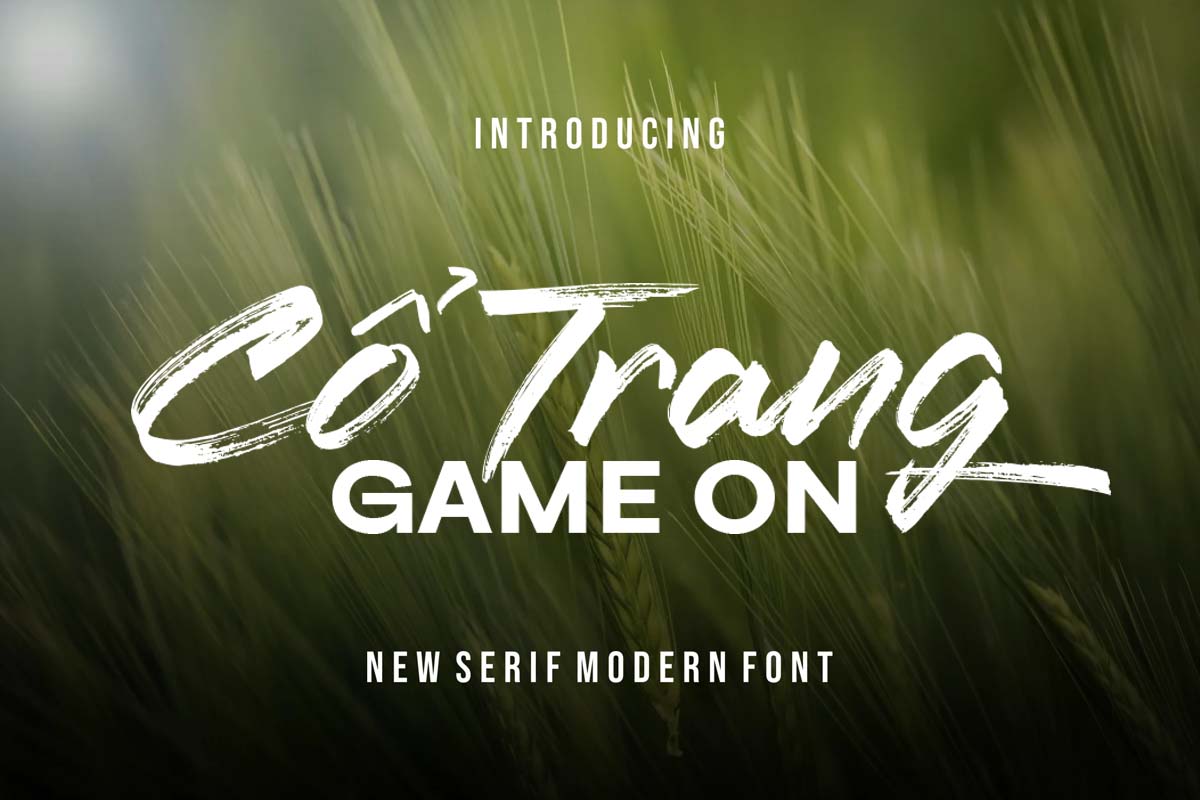
![[Tải Xuống] 13 Font Chữ Nét Cọ Việt Hóa Miễn Phí](https://cdn.s99.vn/cloud/phong-chu-net-co-viet-hoa-anh-6.jpg)
Font chữ nét cọ – hay còn gọi là brush-style font – là dòng chữ được thiết kế mô phỏng theo nét vẽ của cọ vẽ tay, thường có độ dày mỏng không đều, nét quẹt, chảy mực hoặc hiệu ứng thô ráp như thật. Font này mang đậm tính biểu cảm, nghệ thuật và cảm xúc thủ công, tạo nên sự sống động và tự nhiên cho thiết kế.
Khác với font chữ viết tay (script font), vốn thiên về sự liền mạch, uyển chuyển và thanh thoát, font nét cọ thể hiện rõ kết cấu của từng nét vẽ, có thể mềm mại hoặc mạnh mẽ tùy theo phong cách. Sự không hoàn hảo chính là điều tạo nên vẻ cá tính và độc đáo cho loại font này.
Font brush thường được sử dụng trong các thiết kế đòi hỏi sự sáng tạo và cảm xúc – như poster nghệ thuật, typography, tiêu đề nổi bật hoặc các sản phẩm truyền thông mang phong cách thủ công.
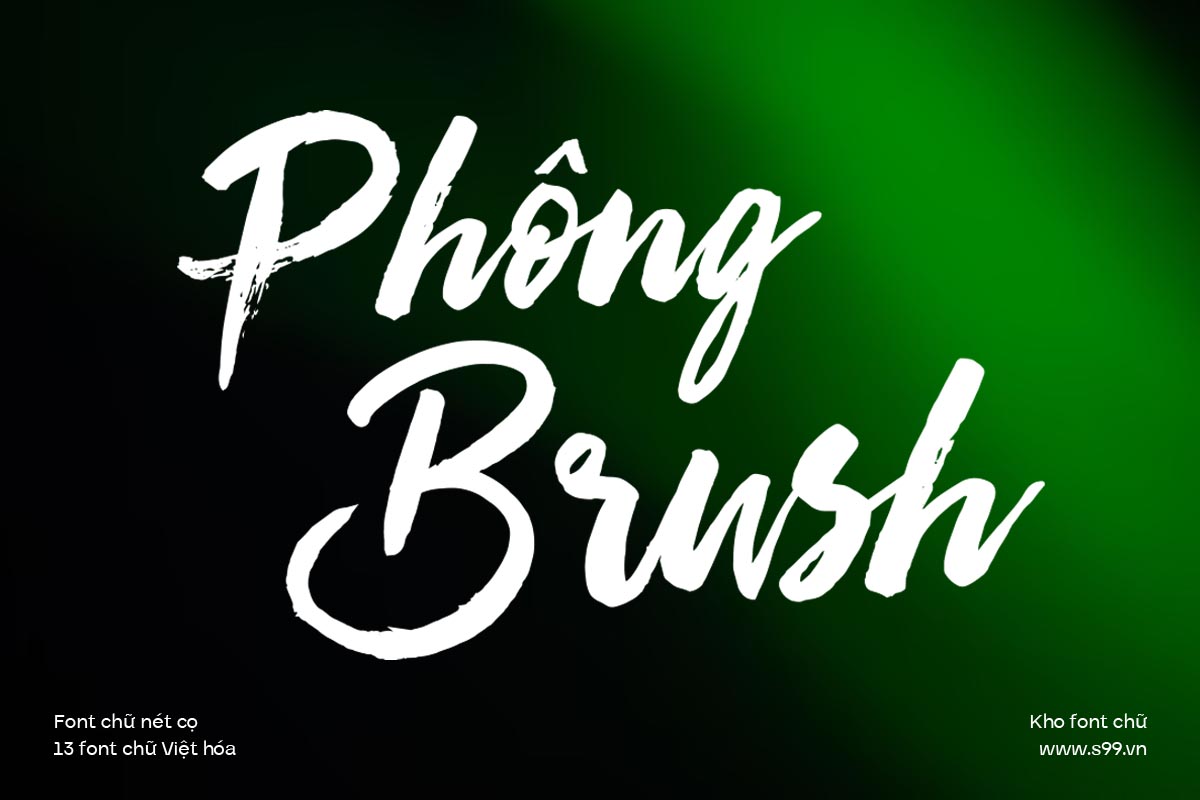
Font chữ nét cọ được xem là công cụ đắc lực cho các nhà thiết kế khi muốn tạo điểm nhấn bằng cảm xúc hoặc hiệu ứng thủ công trong layout. Tuy nhiên, nó không phù hợp với mọi trường hợp – đặc biệt là phần thân bài hay văn bản dài.
Dưới đây là 4 ngữ cảnh nên sử dụng font brush:
Poster phim, sự kiện: Tạo cảm giác mạnh, nổi bật và giàu cá tính.
Thumbnail video, social media: Dễ thu hút ánh nhìn với nét chữ phá cách.
Logo, thương hiệu cá tính: Font brush giúp logo mang cảm giác gần gũi hoặc mạnh mẽ, xưa cũ.
Bìa sách, album, tranh minh họa: Thể hiện đậm chất hình ảnh thủ công.
⚠️ Lưu ý: Font nét cọ nên chỉ dùng cho tiêu đề ngắn, khẩu hiệu hoặc tên sản phẩm. Do kết cấu rối và giàu chi tiết, việc dùng cho văn bản dài sẽ gây rối mắt và làm giảm hiệu quả truyền tải thông điệp.
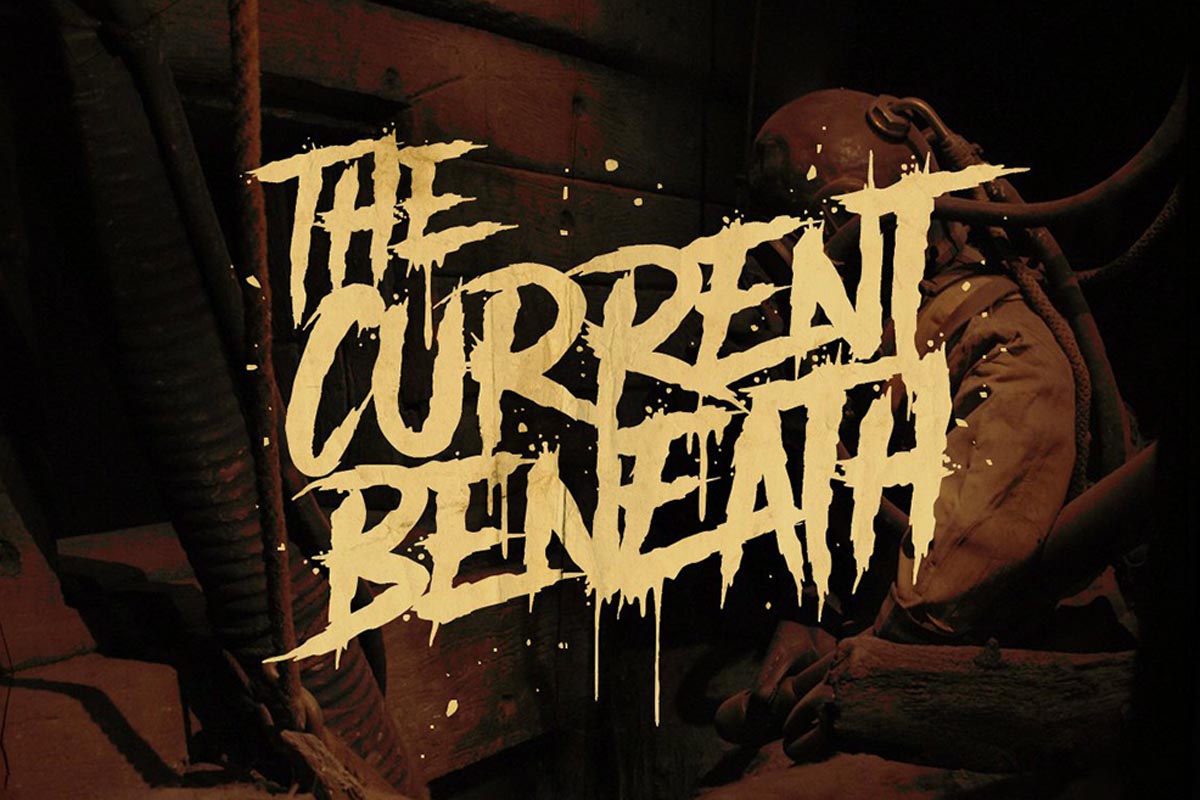
Dưới đây là danh sách 13 font chữ nét cọ đã được Việt hóa, miễn phí tải về, hỗ trợ đầy đủ dấu tiếng Việt.
Font brush đậm, tốc độ, mô phỏng những nét cọ phóng khoáng và dứt khoát như graffiti trên đường phố. Nét chữ bản to, loang nhẹ, phù hợp cho tiêu đề hiphop, poster hành động.
Cấu trúc chữ mạnh, trục nghiêng, như được viết bằng cọ bản lớn dưới áp lực nhanh. Đường nét thô ráp, rạn xước tạo cảm giác bùng nổ. Hợp cho thiết kế âm nhạc, video clip, streetwear.
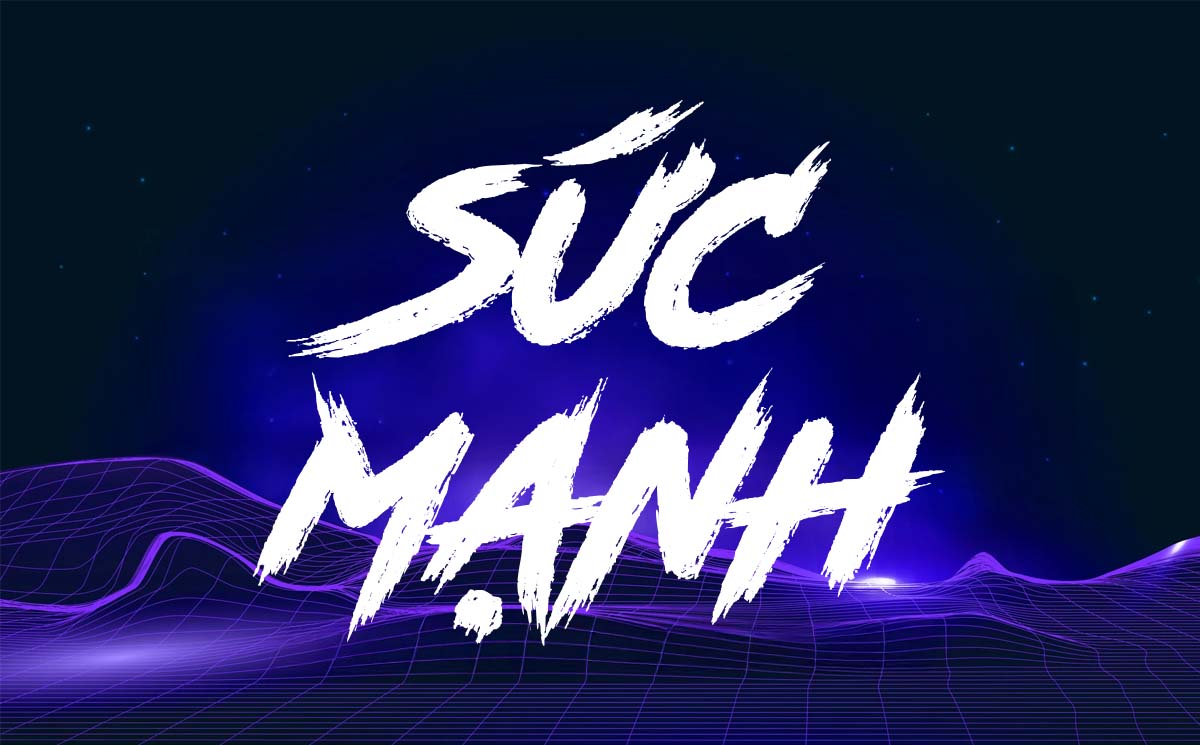
Brush chữ nghiêng, mềm mại, đậm chất handwritten. Nét chữ mượt và có sự đồng đều về độ dày, mang lại cảm giác uyển chuyển, lãng mạn. Lý tưởng cho tiêu đề bìa sách, bài thơ, thương hiệu nữ.
Font nét cọ tròn và nghiêng, chữ viết tay phóng khoáng nhưng vẫn dễ đọc. Các đuôi chữ kéo dài bay bổng, thể hiện sự cá tính, tự do. Dùng tốt cho thiệp, typography nghệ thuật, chữ ký số.
Phong cách brush mạnh mẽ, cảm hứng từ các poster phim kinh dị – hiphop – đường phố. Nét cọ sắc nhọn, nghiêng đậm, nhiều hiệu ứng xé cạnh. Lý tưởng cho banner Halloween, concert, graffiti.
Brush mềm, nghiêng và đều nét, giống bút thư pháp hiện đại. Nét viết uyển chuyển, phù hợp làm thiệp cưới, thương hiệu mỹ phẩm hoặc typography nhẹ nhàng, nữ tính.
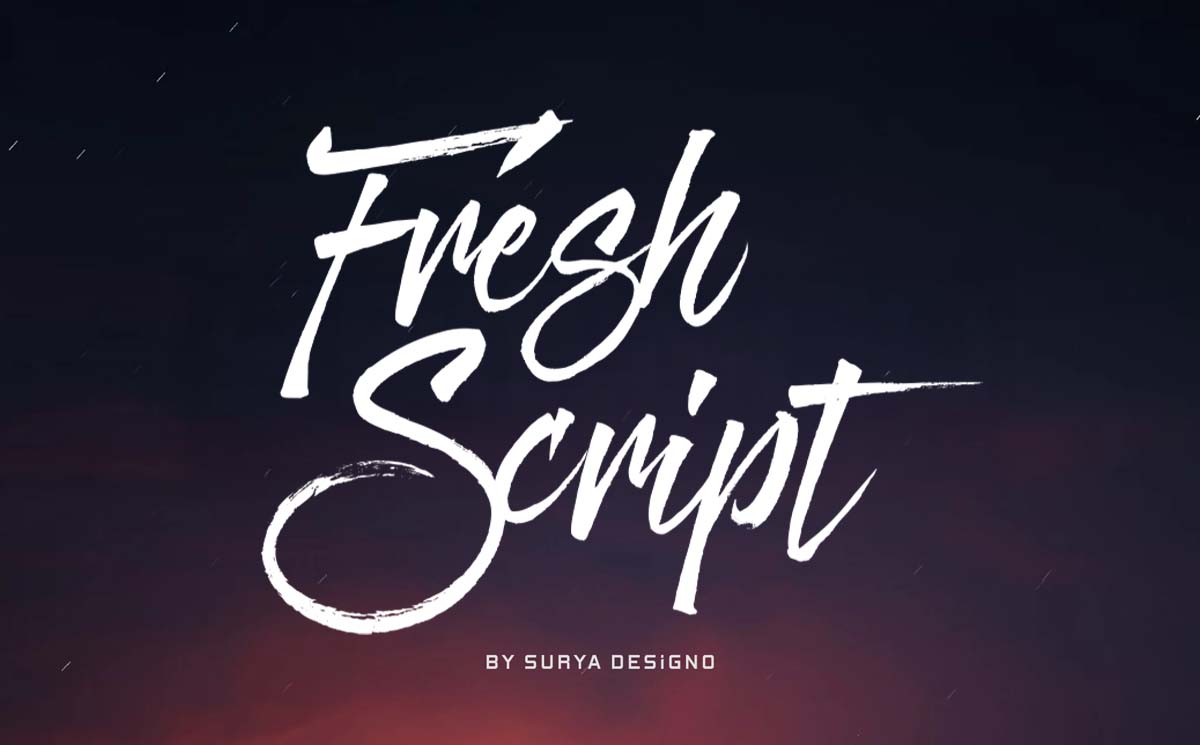
Brush góc cạnh, kết cấu thô, nét như vẽ bằng cọ khô hoặc chổi sơn. Chữ cái thường được bo cứng ở đầu và loang ở cuối nét. Rất phù hợp với poster rock, trailer phim kinh dị, thiết kế phá cách.
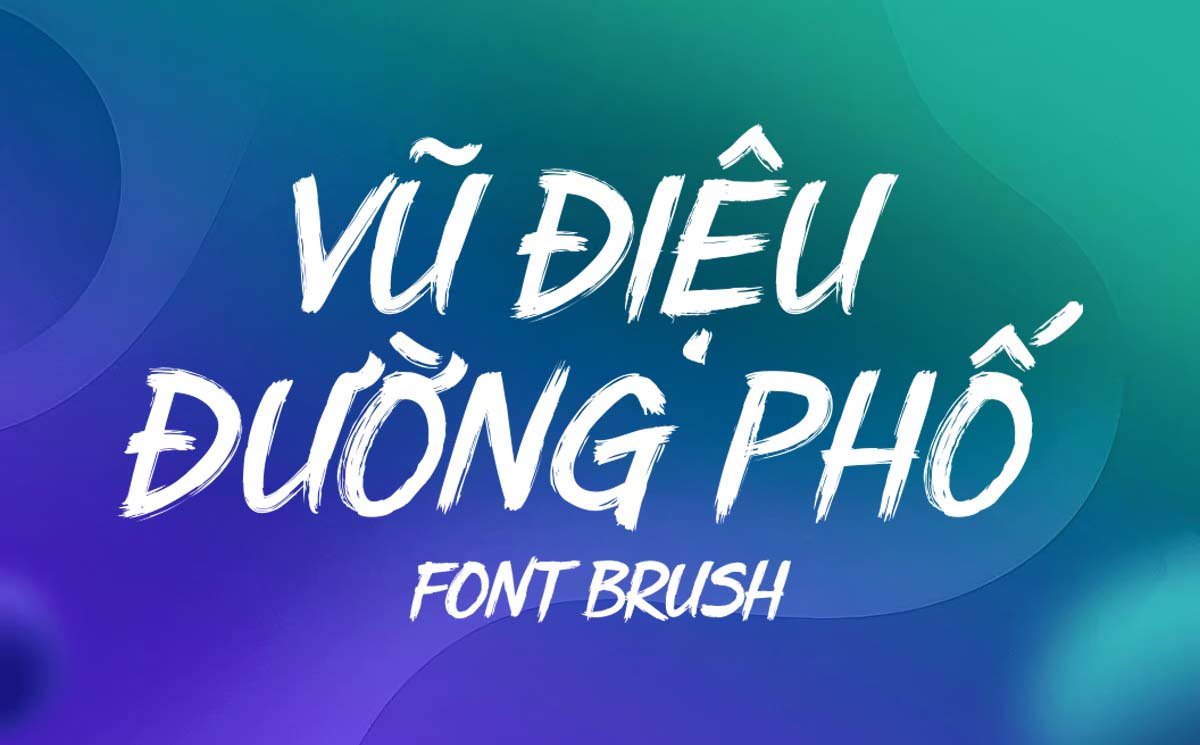
Font brush nghiêng, tạo cảm giác ngẫu hứng như được viết bằng tay trong một lần thở mạnh. Cấu trúc hơi rối, phá cách, nét đậm, cực phù hợp cho video, poster indie, bìa album cá tính.
👉 Tải về SVN DHF Harrys Brush
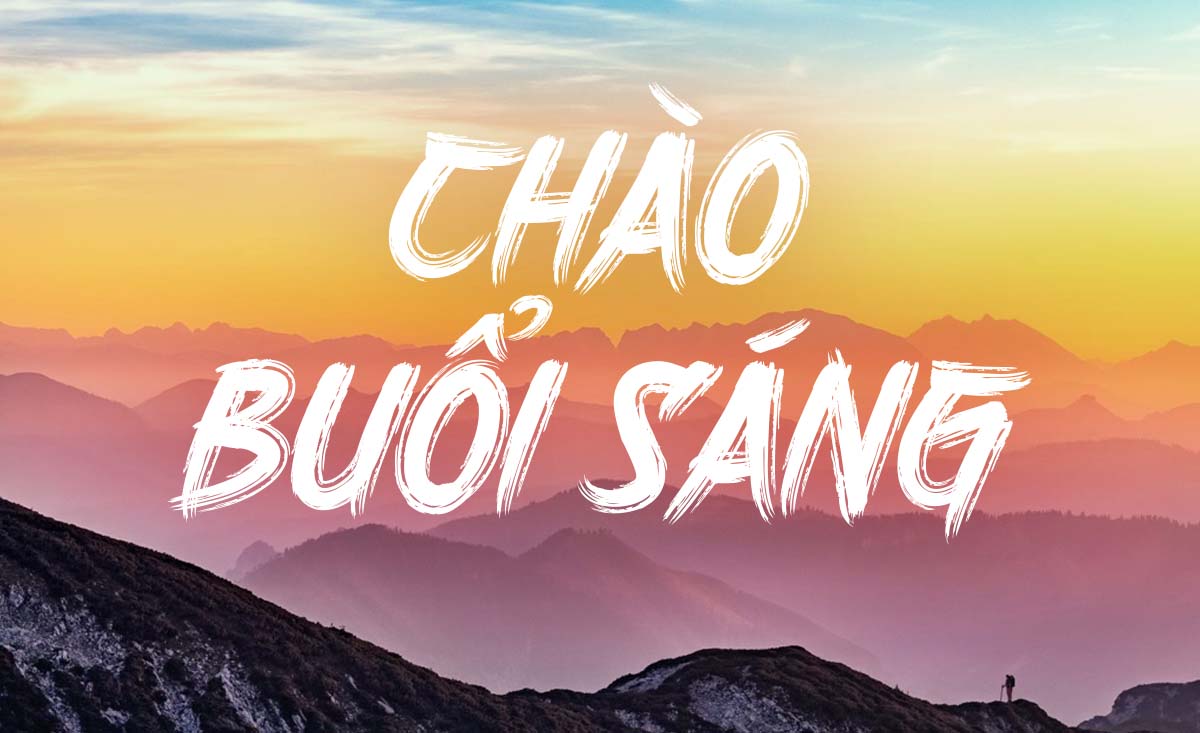
Font thư pháp cao cấp, cấu trúc chữ cái tròn trịa, mảnh mai và rất bay. Các ký tự có độ liên kết uyển chuyển, tạo cảm giác nhẹ nhàng, quý phái. Rất hợp với ngành thời trang, mỹ phẩm hoặc tiệc cưới.
👉 Tải về SVN Boutique Script
Font brush cường lực cao, cấu trúc đậm, đường nét đậm và rách dọc. Kiểu chữ cực kỳ mạnh mẽ, thường xuất hiện trong poster phim hành động, horror, kênh YouTube giật gân hoặc video phân cảnh đặc biệt.
👉 Tải về SVN Another Danger
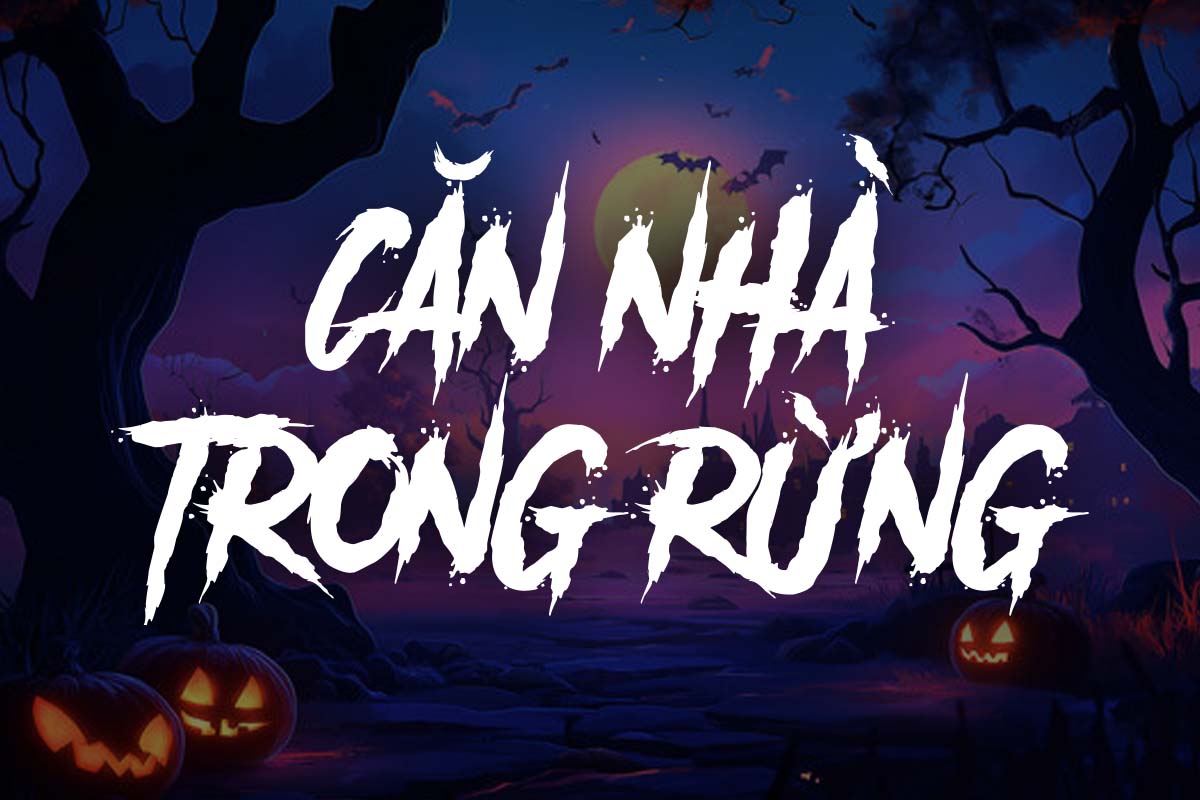
Font brush đậm chất urban, ký tự có độ nhấn mạnh, thô ráp và lởm chởm như phun bằng bình sơn. Rất hợp với thiết kế hiphop, văn hóa đường phố hoặc đồ họa game đối kháng.
👉 Tải về TH Floresh
Font thư pháp mang hơi hướng truyền thống, kiểu nét đại tự xưa với phần thân chữ lớn, chân nét rõ ràng, đậm – mảnh uyển chuyển. Ứng dụng trong thư pháp số, lễ Tết, tranh treo chữ.
👉 Tải về Font Zin
Font thư pháp Việt miễn phí, mô phỏng bút lông thư pháp Huế với lối viết nghiêng nhẹ, nét lượn tinh tế. Rất hợp trang trí Tết, làm thiệp thư pháp, hoặc thiết kế phong cách cổ truyền.
👉 Tải về UTM Thiên Ân
Để font nét cọ phát huy tối đa hiệu quả thị giác, bạn nên kết hợp linh hoạt với các font khác nhằm tạo nên sự đối lập và cân bằng:
Brush + Sans-serif → Dành cho thiết kế hiện đại, như tiêu đề kết hợp mô tả sản phẩm.
Brush + Serif → Phù hợp bìa sách, tiêu đề bài viết dài cần nhấn nhá phần nhìn.
Mẹo: Dùng preview font trước khi áp dụng thực tế. Luôn kiểm tra kỹ các dấu tiếng Việt!
Font chữ nét cọ không đơn thuần là kiểu chữ – nó là công cụ cảm xúc trong thiết kế. Khi được sử dụng đúng cách, brush font sẽ giúp thông điệp của bạn trở nên sống động, chân thực và độc đáo hơn bao giờ hết.
Hãy mạnh dạn thử nghiệm với các tổ hợp font, phối màu, kích thước để tạo nên sản phẩm thiết kế mang dấu ấn cá nhân!